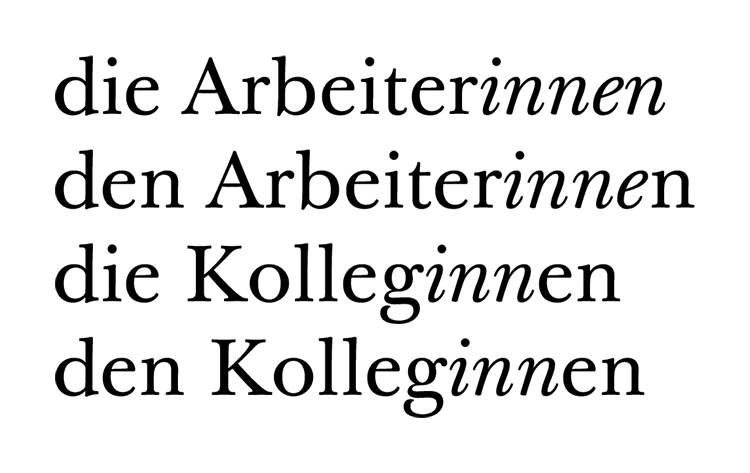
Gender-Schrägstrich
Auf der anderen Seite ist ja genau das rein lesetechnisch ja richtiger, das in den Klammern ist das, was man im männlichen Fall weglassen muss. bei den Gendervirgeln muss man sich dagegen diesen Zusammenhang erst einmal zusammenbastelon, besonders wenn dies aus optischen Gründen grammatikalisch auch noch falsch gemacht wird, wie es in diesem Fall ja gewollt ist. Wenn ich solche Texte dann lesen muss, wird wiederum viel zu viel Energie im Entschlüsseln der Gender-Rätsel eingesetzt, und der Rect vom Text fällt unter den Tisch. Hierher weiß man gar nicht, worom es letztlich geht. Da wär es - auch wenn es mehr Platz braucht ein "Kolleginnen/Kollegen" im Wechsel mit "Kollegen/Kolleginnen" die bessere, und deutlich weniger ausklammernde Lösung.
ja, ich vermutete schon, dass die klammern für wenig applaus sorgen, wollte sie aber doch mal genannt haben. noch ein vorschlag: die arbeiterinnen, den arbeiterinnen, die/den kolleginnen – also, falls man das hier nicht gut sieht, jeweils die teile des wortes kursiv stellen, die zur bildung der weiblichen form benötigt werden. in der richtigen schriftart, die eine deutliche kursive hat, könnte das funktionieren. hier als beispiel die baskerville:
oder ist das auch schlecht, weil die kursive heutzutage einer der aufrechten untergeordnete rolle einnimmt?
und sind die varianten ›die arbeiter/arbeiterinnen‹, ›den arbeitern/arbeiterinnen‹, ›die/den kollegen/kolleginnen‹ (und umgekehrt) usw. ausgeschlossen?
oder ist das auch schlecht, weil die kursive heutzutage einer der aufrechten untergeordnete rolle einnimmt?
Mir gefällt die Lösung gut! Man könnte ja im Falle eines kursiven Absatzes das Prinzip umkehren – also »die/den Kolleginnen«.  ;-)
Aber kommt dann nicht das Missverständnis auf, man wolle das "innen" besonders betonen?
Weil oft benutzt man ja Kursive, um die Betonung auf etwas zu legen.
Langsam freunde ich mich mit dem Gedanken an, dass unsere Sprache auch völlih genderneutrale Varianten solcher Bezeichnungen braucht, und dass man da so etwas wie Kollega, Mitarbeita, Arbeita usw erdacht hat, dazu viewlleicht noch einen genderneutralen Artikel de, statt der, die, das?
Schließlich kommt ja dann noch hinzu, das bei der ganzen Gendervirgelei ja eine (wenn auch kleine) Gruppe total vernachlässigt wird, nämlich die jeniigen, die sich weder als Männlich noch als Weiblich verstehen, oder beides gleichzeitig sind.
Irgerndwie habe ich allerdings das gefühl, dass durch diesen Wunsch zur Gleichstellung, den ich grundsätzlich ja akzeptiere, letztlich nur zusätzliche Ausgrenzung geschaffen wird. Fruher gehörten, sprach ich über meine Kollegen die weiblichen ganz selbstverständlich hinzu, jetzt muss ich über Kollegen und Kolleginnen reden, also sie sprachlich auseinander sortieren.
Fruher gehörten, sprach ich über meine Kollegen die weiblichen ganz selbstverständlich hinzu, jetzt muss ich über Kollegen und Kolleginnen reden, also sie sprachlich auseinander sortieren.
ob kolleginnen wirklich dazugehören, nicht nur ›mitgemeint‹, sondern auch vom hörer mitgedacht werden, wenn man über ›kollegen‹ spricht – das ist ja genau die frage, an der sich diskussionen entzündeten, aufgrund derer es zu verschiedenen formen der ›beidnennung‹ kam. diese diskussionen zu ignorieren und zu fragen, warum man nicht beim status quo ante geblieben sei, erscheint mir ein bisschen simpel.
Ich stimme auch catfonts zu, dass das früher sicher unproblematischer war, weil es ja auch nicht problematisiert wurde.
Aber dir, Thierry, muss ich auch zustimmen, jetzt sind halt die Diskussionen drüber da, und man muss sich mit ihnen auseinandersetzen.
Es ist ja so wie mit vielen Problemen, dir wir heute haben: Die sind alle hausgemacht. Ein Gedanke zu viel und schwupps! hat man ein neues Problem entdeckt, das man so schnell nicht mehr losbekommt. Dann kann man eben nicht mehr sagen: Tun wir so, als ob es nicht da wäre.
Das inn kursiv zu setzen, wäre für mich eine subliminale Aufforderung, mal wieder ein Bier trinken zu gehen...
Doch doch, Kollegen war vom Verständnis her schlichtr eine Untergruppe der Menschen, die mit einem zusammen im gleichen Betrieb, der gleichen Abteilung, oder wenn man möchte in der Brigade mit einem zusammen tätig waren, da gehörten dann eben sowohl Männer als auch Frauen dazu. Wollte man die Frauen ausschließen, weil irgend etwas die Männer betraf, weil man sich z.B. mit diesen zu einer typisch männlichen (?) Freizeitgestaltung treffen wollte, sprach man von "männlichen Kollegen", während die "weiblichen Kollegen" sich dann anderen Dingen zuwandten.
In die übergreifende Gruppe der Kollegen gehörten dann eben auch die, von denen man nicht so ganz sicher war, ob man sie nun zu den männlichen, oder zu den weiblichen zählen sollte, aber das wollte man, war dieser Mensch sonst ein guter Kollege auch gar nicht so genau wissen (allerdings tuschelten dann einige, die das dann eben doch besser wussten)
Nachdem man jetzt die Kollegen in Kollegen (automatisch und nur männlich) und Kolleginnen (die andere Sorte) sortiert hat, befürchte ich, dass wir bald auch von Menschen und Menschinnen sprechen müssen,
Lach! Das hat bei genauem Hinsehen aber ziemlich weibliche Kurven, oder …?  :party:
Also am linken Ende des unteren Bogens erkenne ich eine stehende Serife! Pfui! Das in einem öffentlichen Forum! *d&r* ;-)
nur das ẞ haben wir da bisher nicht untergebracht :-(
Lach! Das hat bei genauem Hinsehen aber ziemlich weibliche Kurven, oder …?  :party:
Es sieht ziemlich schwanger aus. Das beruhigt mich, das ß stirbt also doch nicht aus.